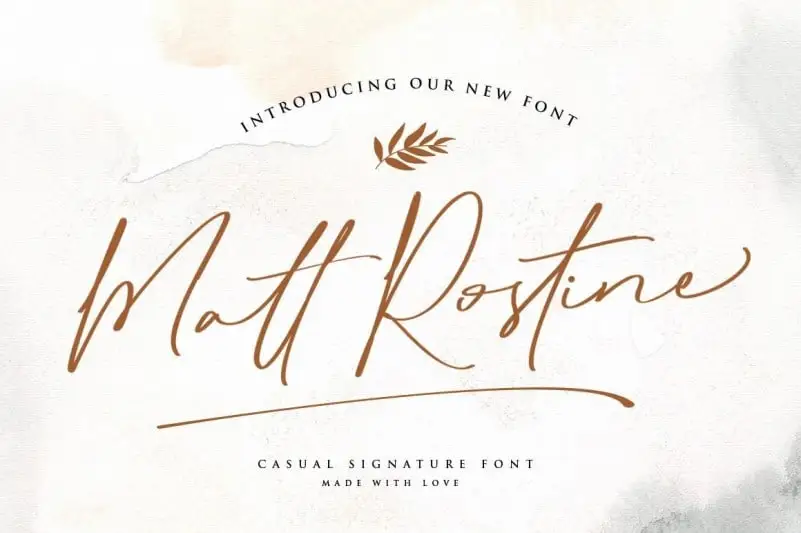
Matt Rostine Handwritten Font – Download Grátis
A fonte “Matt Rostine Handwritten Font” é uma escolha ideal para aqueles que buscam um touch elegante e único em seus projetos digitais. Inspirada na autenticidade das letras escritas a mão, esta fonte traz uma textura natural e um toque de luxo à qualquer design. Desenvolvida pela Vultype através da plataforma 99designs como um Luxury Script Font, ela oferece uma aparência encantadora que se adapta perfeitamente a aniversários de casamento, cartas de agradecimento, citações, cartões de felicitação e até mesmo aos logotipos e cartões de visita. A fonte “Matt Rostine Handwritten Font” não apenas adiciona um toque personalizado a qualquer design onde for usada, mas também dá uma sensação única e sofisticada que se torna irresistível em sua identidade visual. É perfeita para quem deseja transmitir mensagens de forma autêntica, sem perder o respeito pelo bom gosto elegante que essa fonte traz consigo.